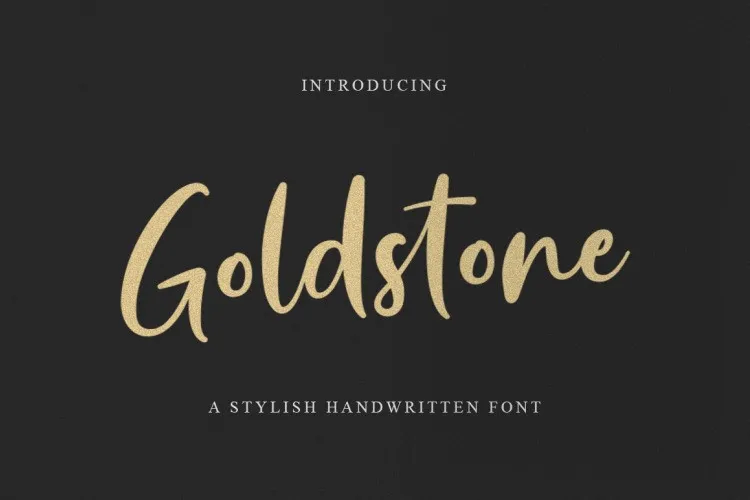
Goldstone Script Font – Download Grátis
A Goldstone Script é uma fonte calligráfica moderna com estilo único, criada para artistas visuais que buscam adicionar um toque elegante e sofisticado a seus projetos. Este é mais do que apenas outra fonte de texto; ele oferece um nível interativo através de sua magia de pressão, permitindo que você crie expressões sutis que se misturam naturalmente à letra principal. A Goldstone Script apresenta uma elegante assinatura, com alternativas perfeitas para combinar e adaptar conforme necessário. Com seu design casual e único, a Goldstone Script é ideal para uso em assinaturas, embalagens de papel, logotipos, citações na publicidade ou no livro, capas de revistas ou livros, roupas, marcas de marca e até mesmo embalagens de produtos. Este moderno ícone da calligrafia é perfeito para quem busca criar um visual único e atraente em qualquer projeto que esteja trabalhando.